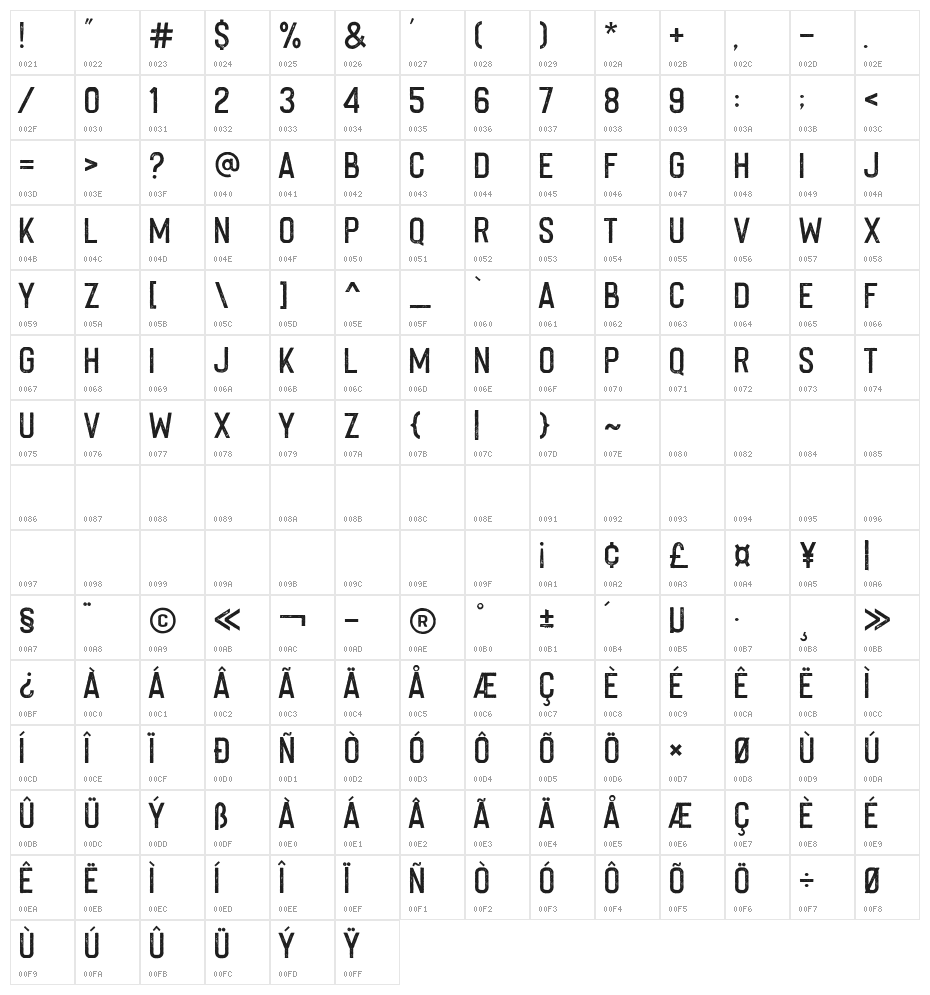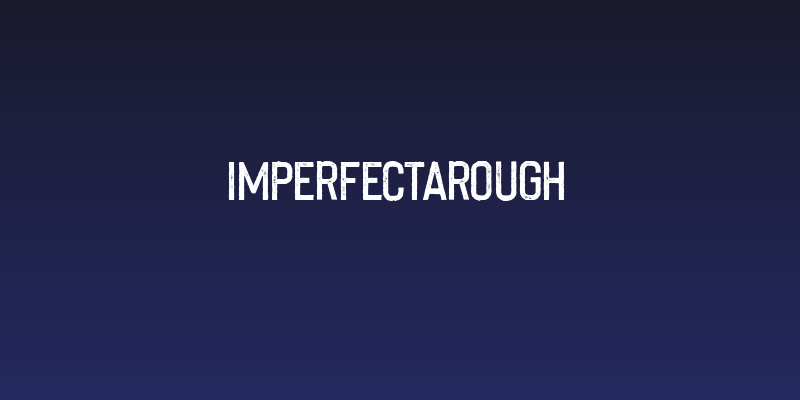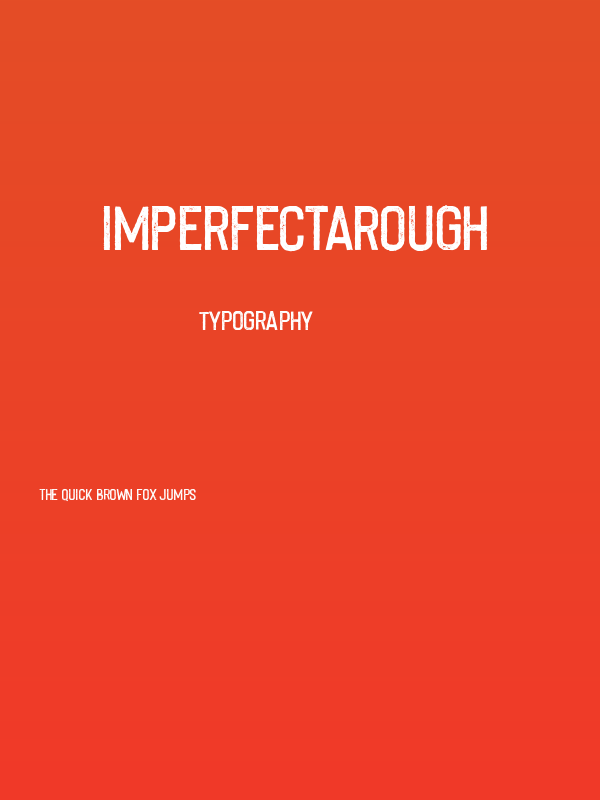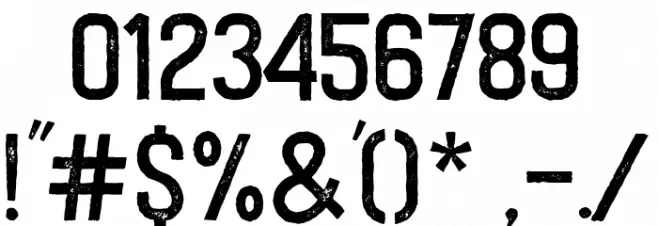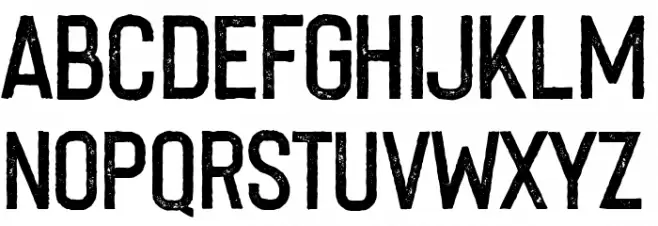
ImperfectaRough Font
| عائلة الخط | Imperfecta Rough |
| الفئات | Messy |
| النمط العام | Vintage |
| مشاريع مقترحة | Ideal for vintage posters, industrial-themed designs, branding for rustic products, or any project needing a bold, textured aesthetic. |